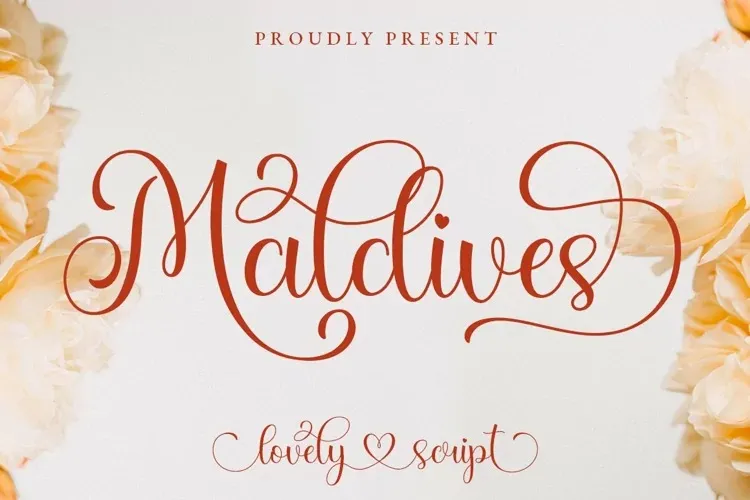
A Maldives Font é uma elegante tipografia feita para designers apaixonados por letras fluidas e românticas. Ela surgiu do talentoso Typesthetic Studio, um designer de letra que criou este estilo script perfeito para uma variedade de projetos gráficos como logotipos, estaçãoamento wedding, cartões de presentes, embalagens de produtos fotografias, marcas de água e citações escritas à mão. A Maldives inclui 6 setinhos estilísticos encantadores: alternativas entre maiúsculas e minúsculas, juntas deslizantes de letras pequenas que contêm corações, pontas iniciais e finais de letras minúsculas e duas opções de junção de ascentes e descendentes. Além disso, a fonte apresenta todos os caracteres maiúsculos e minúsculos, símbolos multilinguísticos, números e sinais de pontuação, além de ligaturas. Ela é perfeita para aqueles projetos que valorizam uma atmosfera natural e romântica, tornando-a ideal tanto para designers profissionais quanto iniciantes.